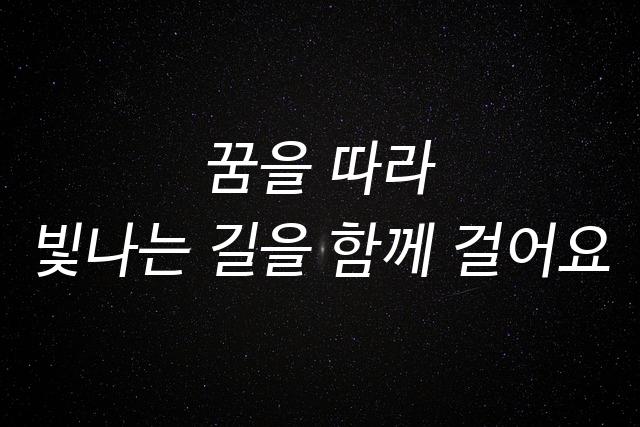
팔칠엠엠 일상 보통 폰트는 단정하고 깔끔한 고딕 스타일로 제작되어, 일상적인 사용에 적합하며 기본적인 디자인의 특성을 갖고 있습니다. 이 폰트는 현대적 감성을 담아내는 데 최적화되어 있습니다.
팔칠엠엠 일상 보통은(는)
기본 고딕, 감성적인, 부드러움 계열의 생김새를 가지고 있으며
웹/앱 디자인, 프레젠테이션, 보고서/문서 등에서 자주 활용되며, 효과적인 메시지 전달에 적합합니다.
이 폰트는 출판/미디어, 크리에이티브, 기술/IT 분야에 잘 어울리며,
명확한, 편안한, 단순한 느낌을 담고 있는 것이 특징입니다.